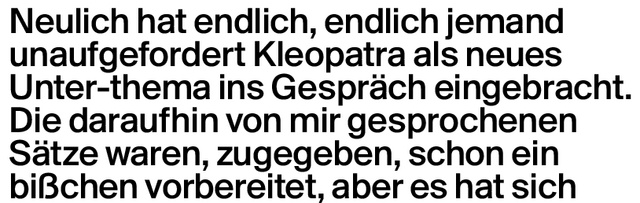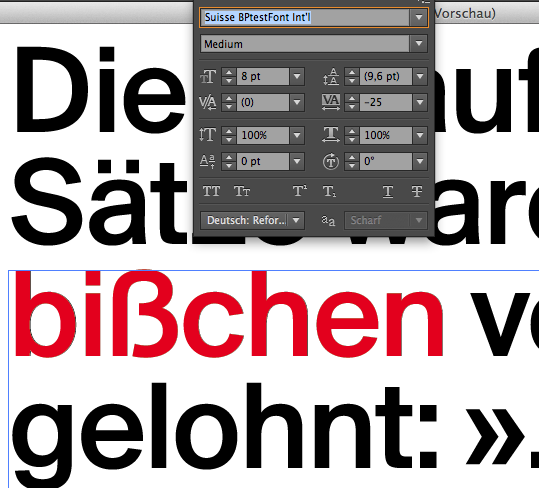
Nicht Helvetica, nicht Frutiger, irgendwie Grotesk aber welche Schrift genau ist das?
ich bin zwar erst seit einigen Stunden angemeldet, hätte aber schon gleich eine Frage.
Welche Schrift könnte die im Anhang gezeigte konkret sein?
Wurde das Bildschirmfoto von einem pdf gemacht? Dann drück mal ⌘D und schau bei Schriften nach … Wenn das kein pdf war: Woher stammt das?
den guten Tipp mit apfel-d habe ich probiert, leider ist die Registerkarte Schriften leer.
Der Text lässt sich auch nicht auswählen. Scheinbar wurde er in Pfade gewandelt.
Die PDF Datei erhielt ich von einer ehemaligen Freundin, deshalb ist es auch leider nicht möglich einfach zu fragen.
Auch whatfontis und Konsorten konnten mir nicht zufriedenstellend helfen.
Gibt es noch irgendwelche Tricks?
Wow, R::bert!
Oder wie wir Hanseaten zu sagen pflegen: »Ich bin derbe beeindruckt.«
Ich habe mir den Testfont heruntergeladen und ein wenig herumgespielt. Siehe da: es passt perfekt.
Wie konntest du das so schnell herausfinden? Ich beiße mir daran nun schon seit Montag die Zähne aus.
Och, so ein Gefühl … es gibt so Stile in der Formensprache, die lassen sich ab und zu Nationalitäten oder gar Foundries zuordnen. Hier hat es eben mal hingehauen :roll:
Wenn es nach Schweiz ›aussieht‹, sind Lineto, B+P und Optimo eigentlich immer die ersten Adressen, bei denen man nachschauen kann.